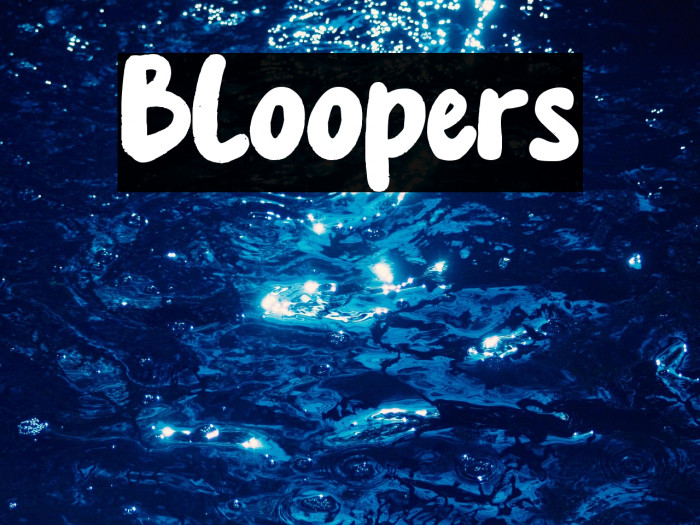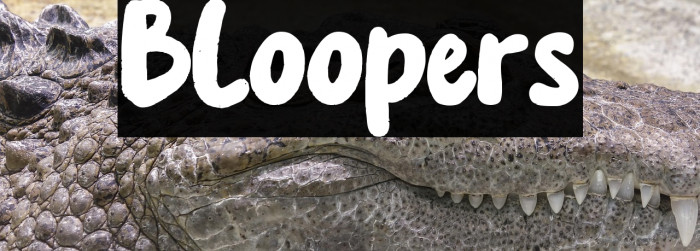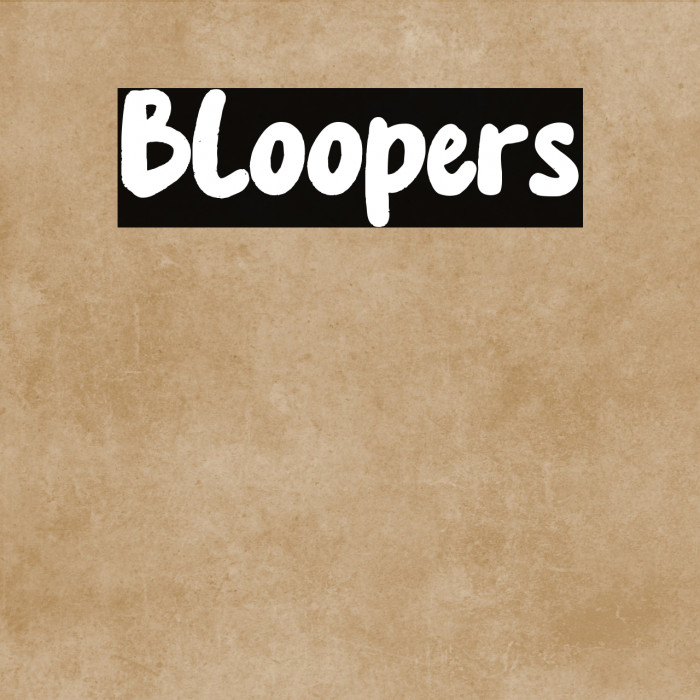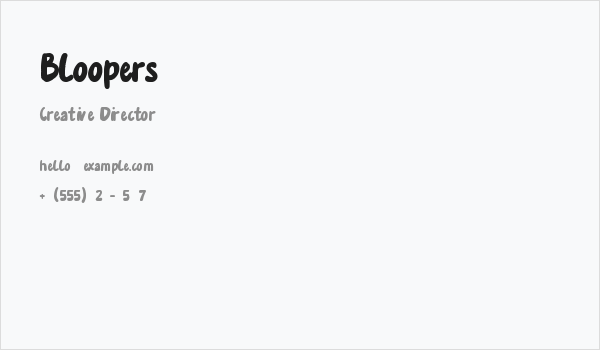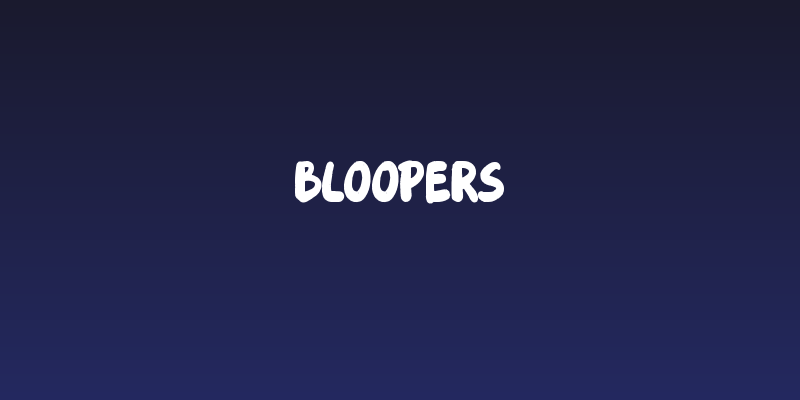
Bloopers Font
| Caso d'uso | Headlines, Logos, Informal Text |
| Progetti proposti | Ideal for children's books, comic strips, playful branding, and casual invitations. |